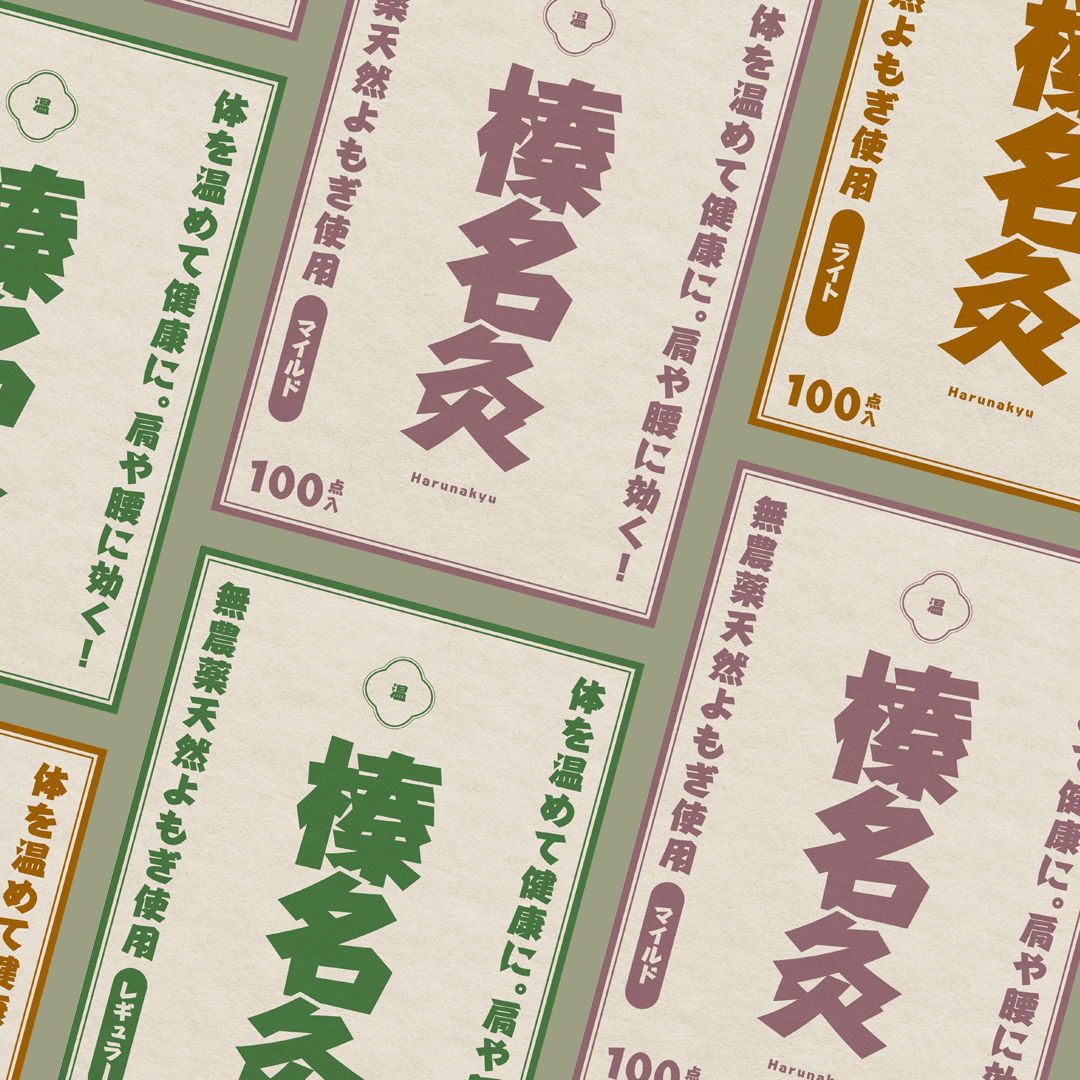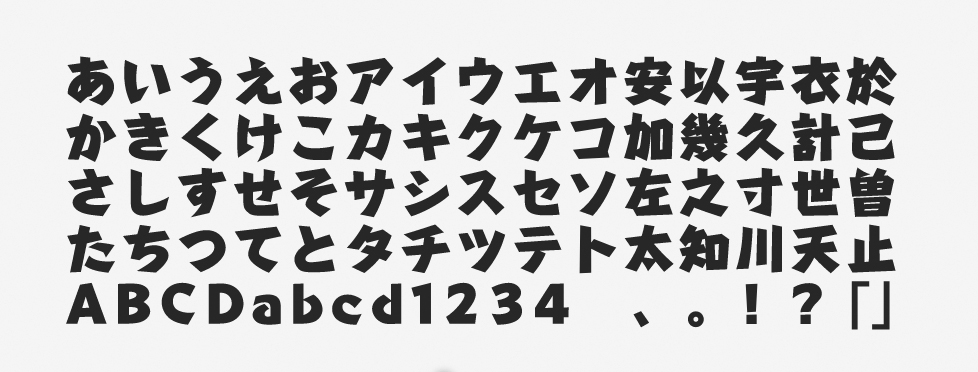
「ハルクラフト」について
ハルクラフトは、行書や草書の筆勢を取り入れた大らかな文字をベースとしたフォントです。力強いインパクトとともに、人間らしい温かみも感じさせます。パワフルで無骨ながら、ややポップな印象を与えられることが魅力。タイトルやロゴ、キャッチコピーなど、大きな級数の文字で特に使いやすいフォントです。
「ハルクラフト」の特徴
両端を鋭くカットしたエレメントも特徴的で、肉声を聞くような動きと表情、独特な味わいも表現されています。極太なフォントであるため、とにかく目立ちやすくてインパクトも絶大です。その設計上、ハルクラフトで文字を組むと、レイアウトには「十分な黒み」が生まれます。
あえて文字の間隔をツメ気味に組むと、その魅力がより高まります。親しみを感じさせやすいため、無機質なコンテンツのデザインには不向きで、勢いのある表現に適しています。
画像とテキストを組み合わせて構成する「ディスプレイタイプ」の形式で使いやすいフォントです。今回の作例では、最も目立たせたいロゴの3文字の隙間を埋めるべく、食い込ませるくらいツメて一体感・一塊感を演出しました。少し重ねた事で、ロゴタイプとしての雰囲気がグッとアップしたと思います。
タイトル・見出し、商品パッケージ、ロゴ、ラベル、POP
「ハルクラフト」の書体情報